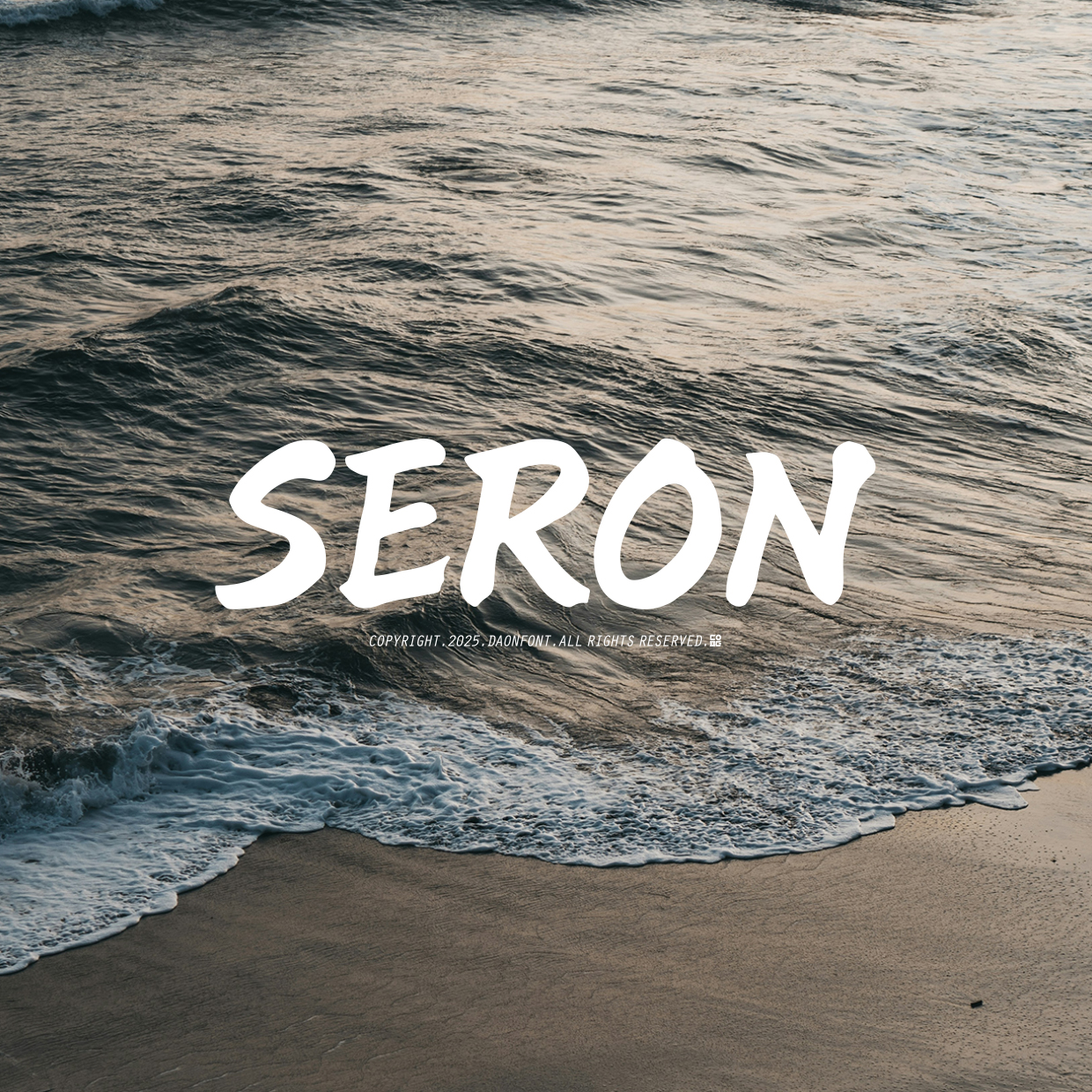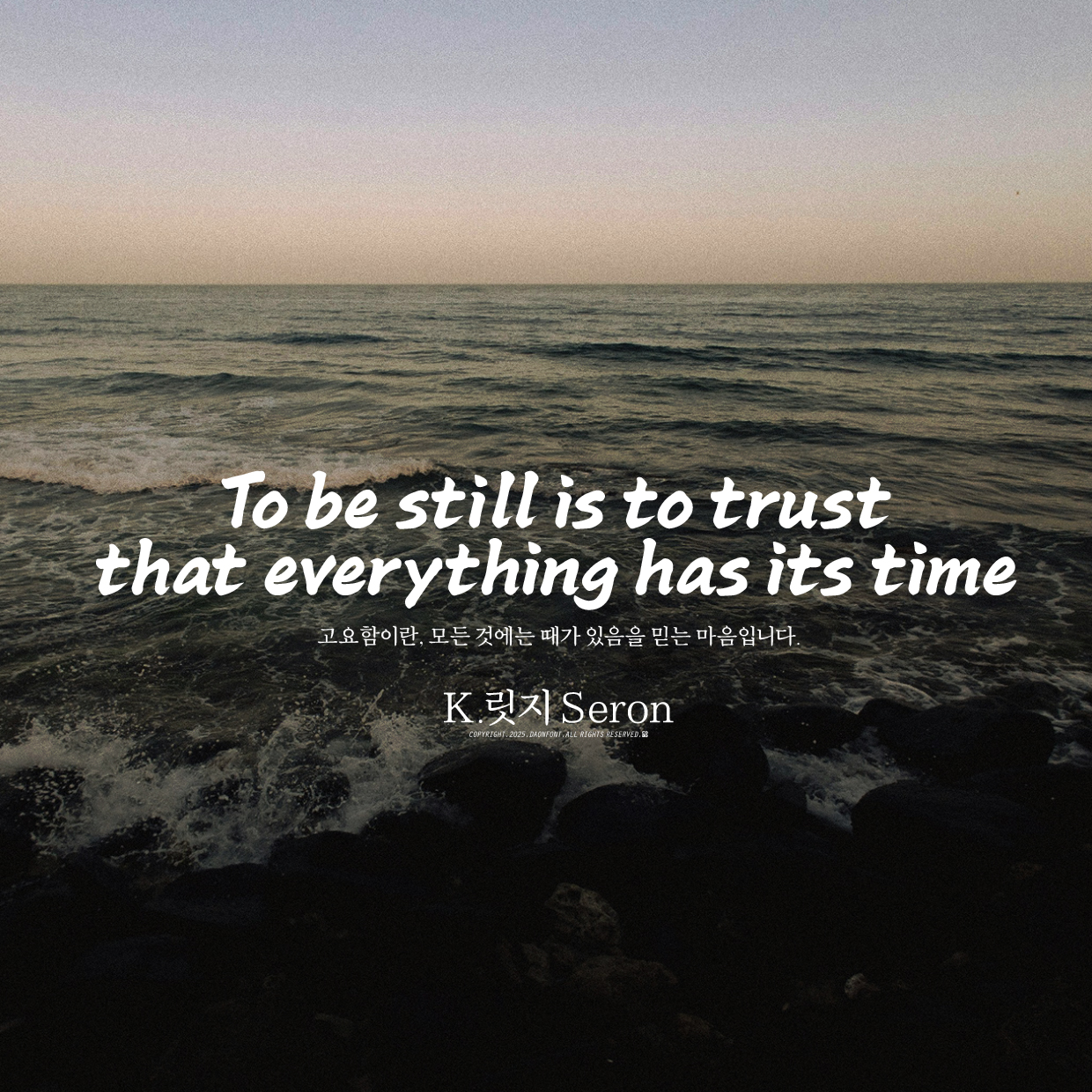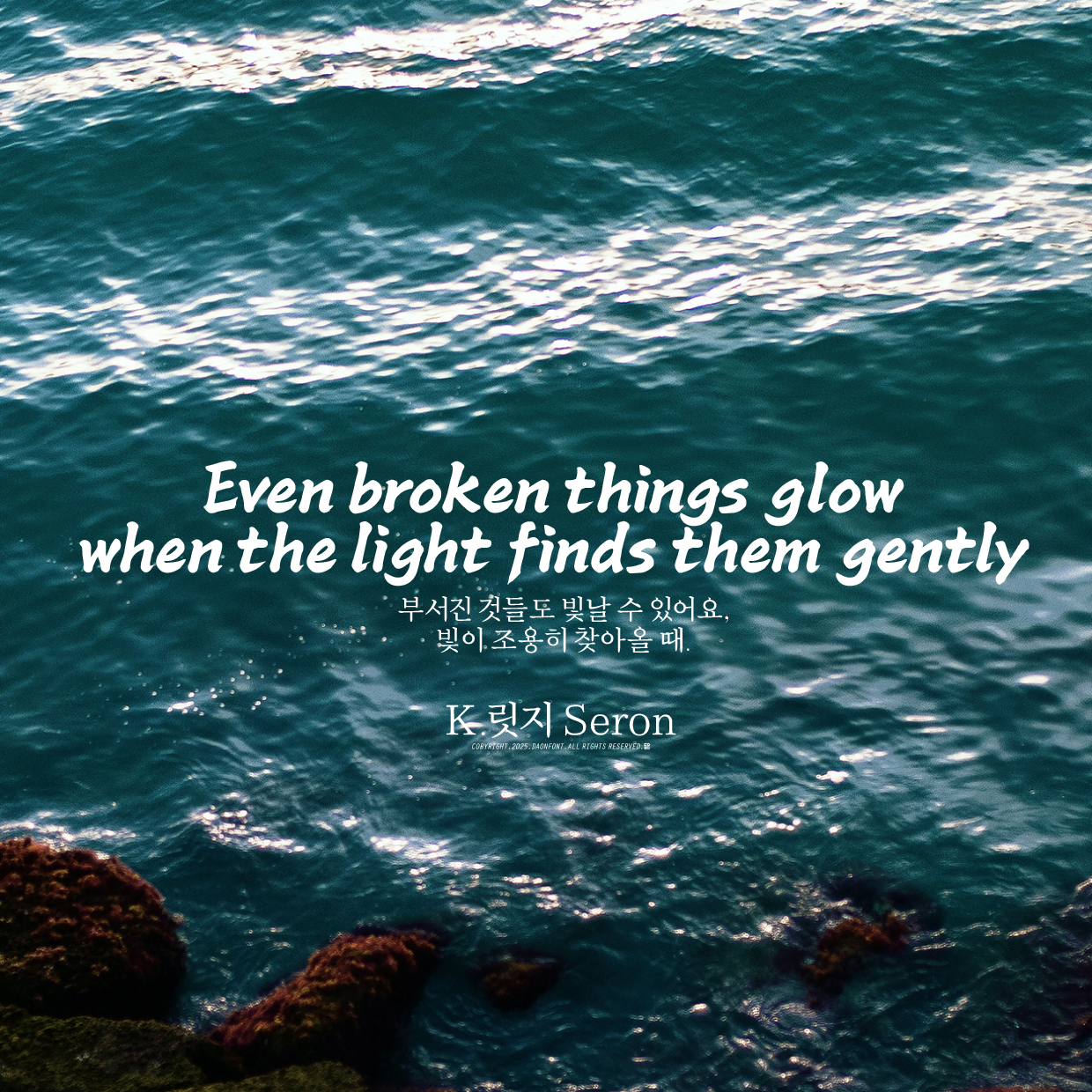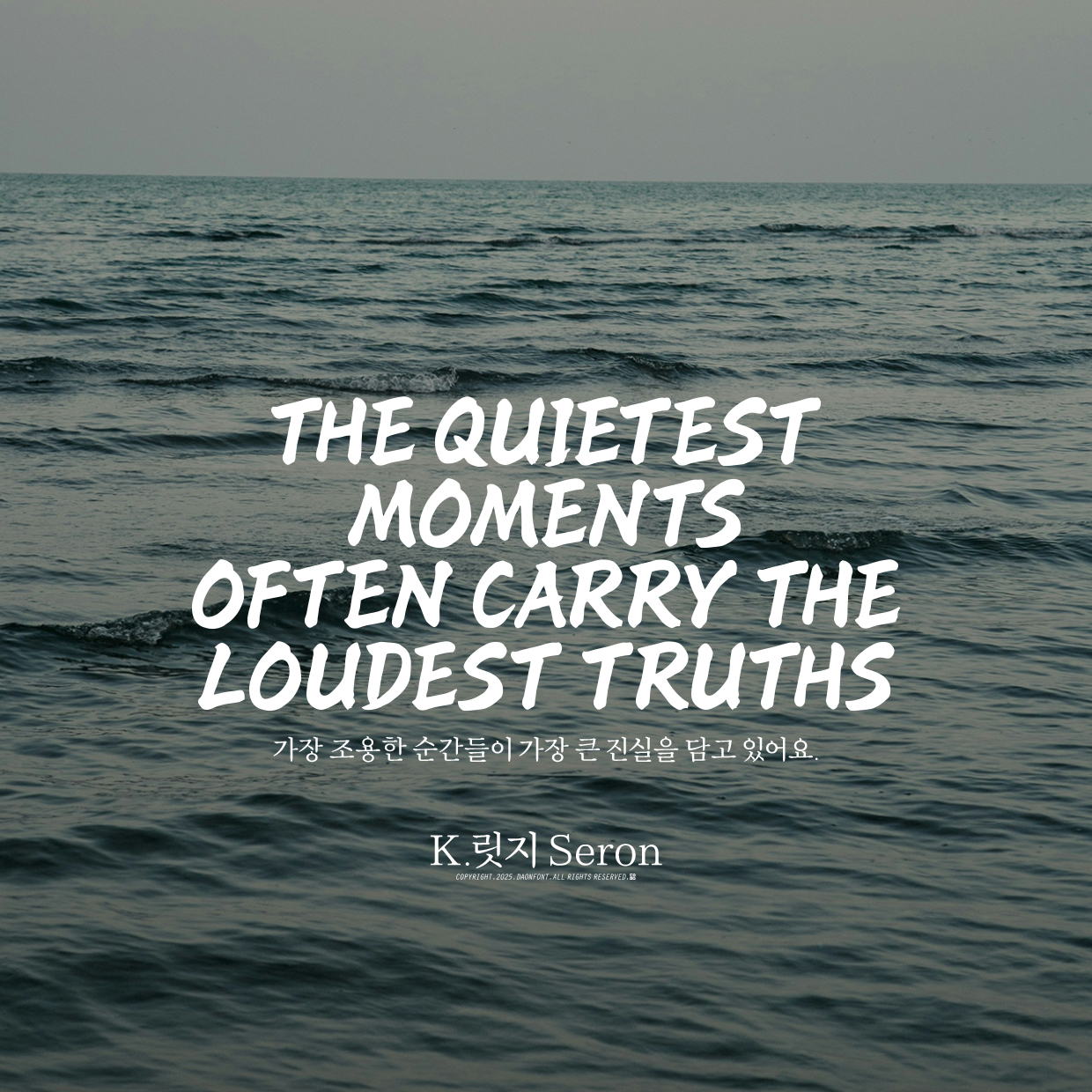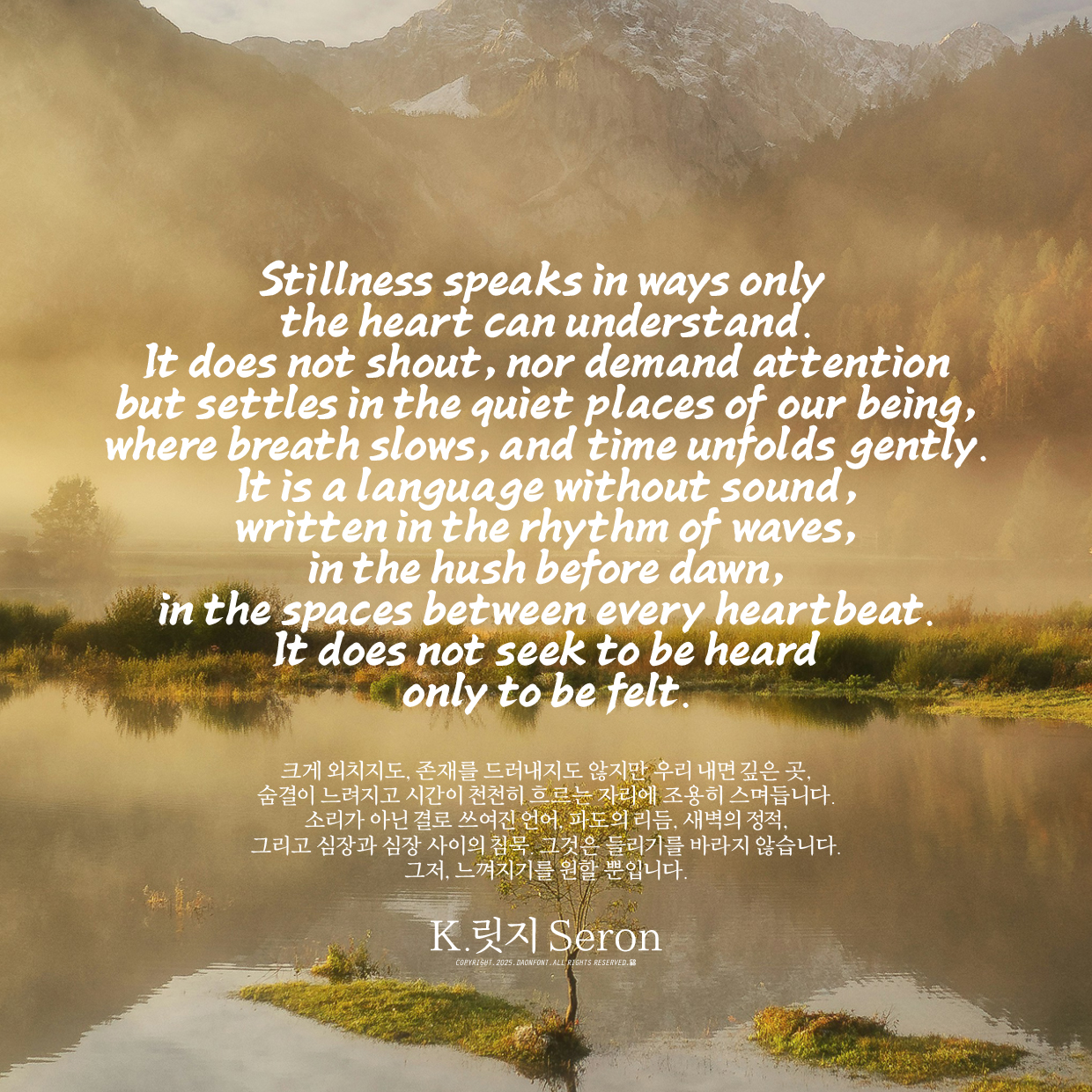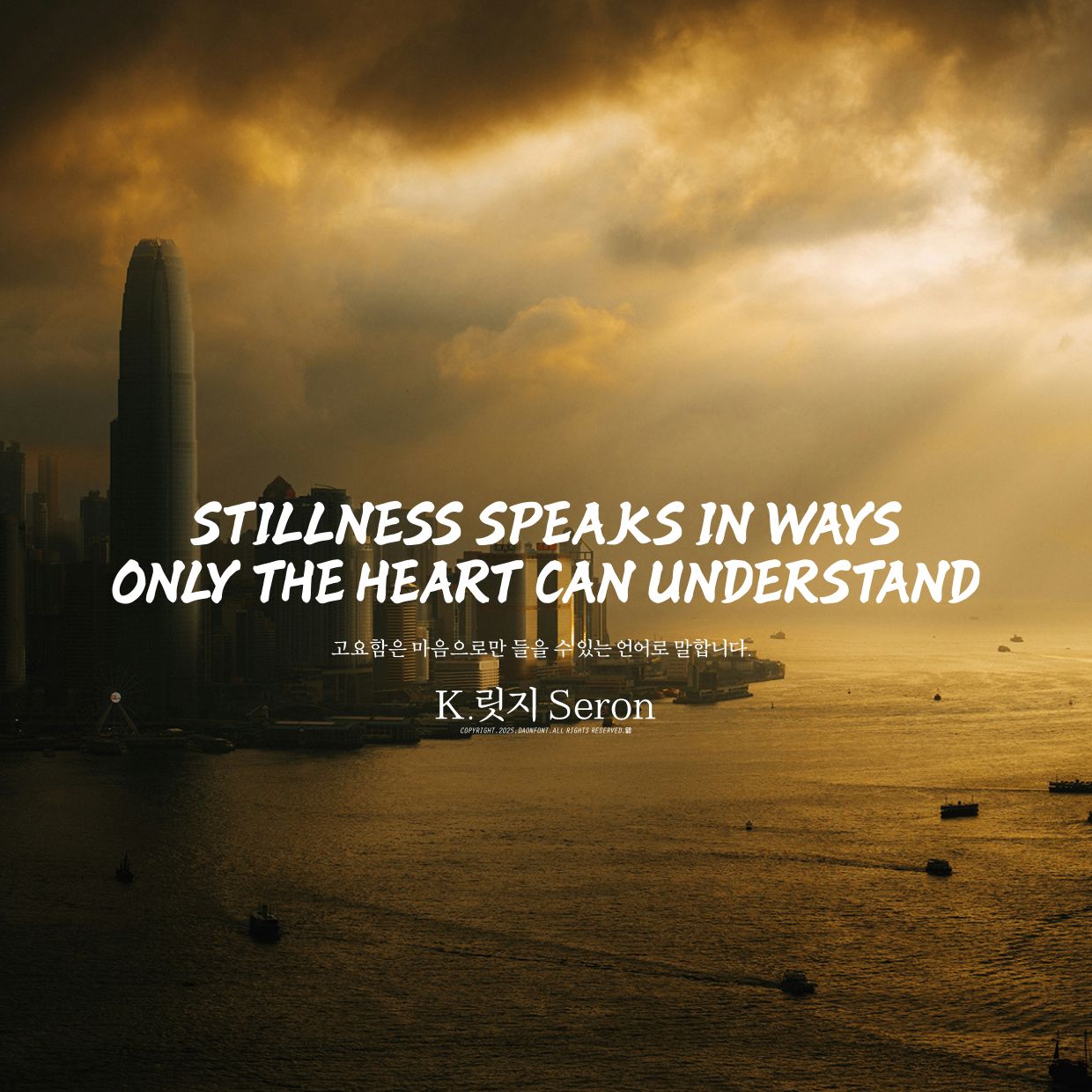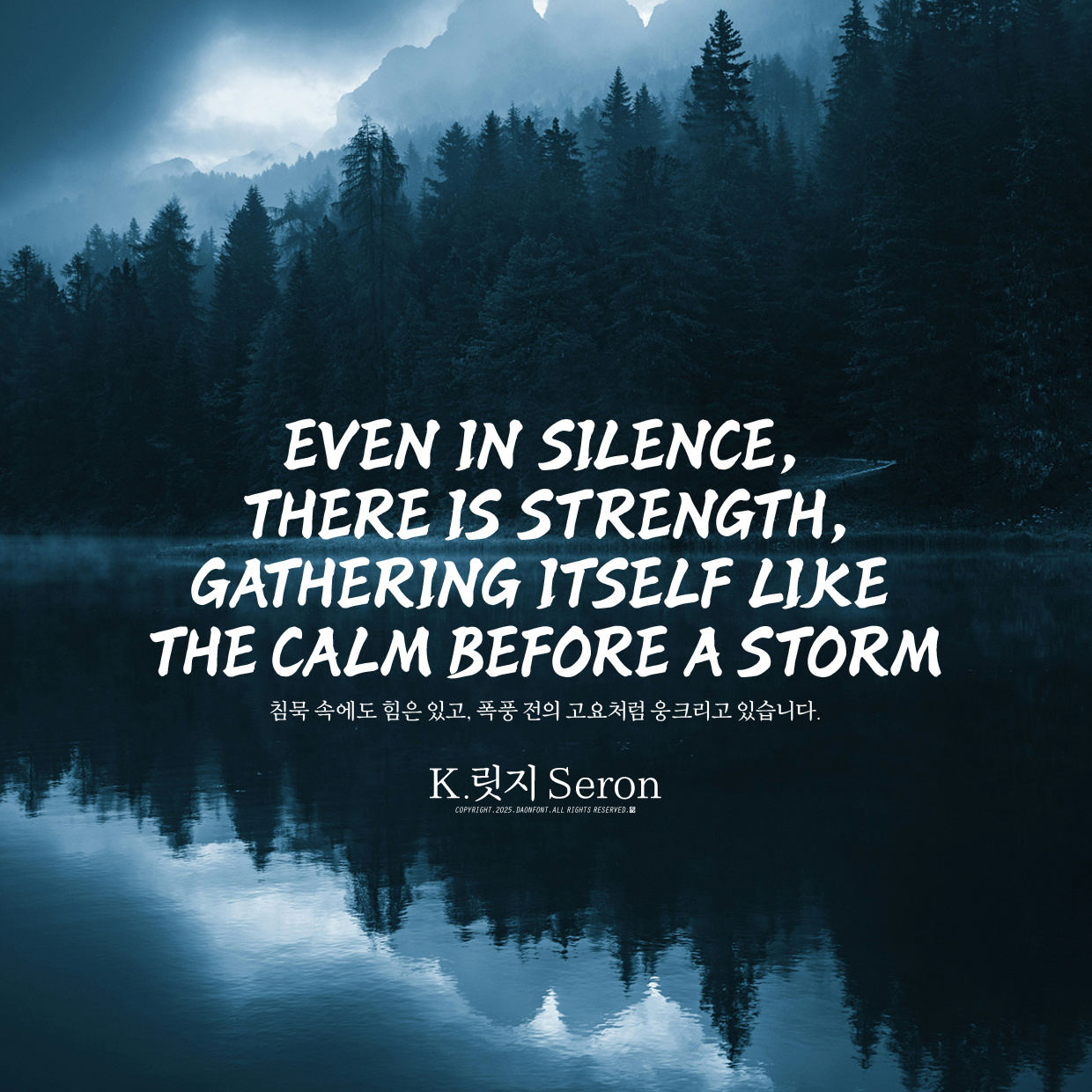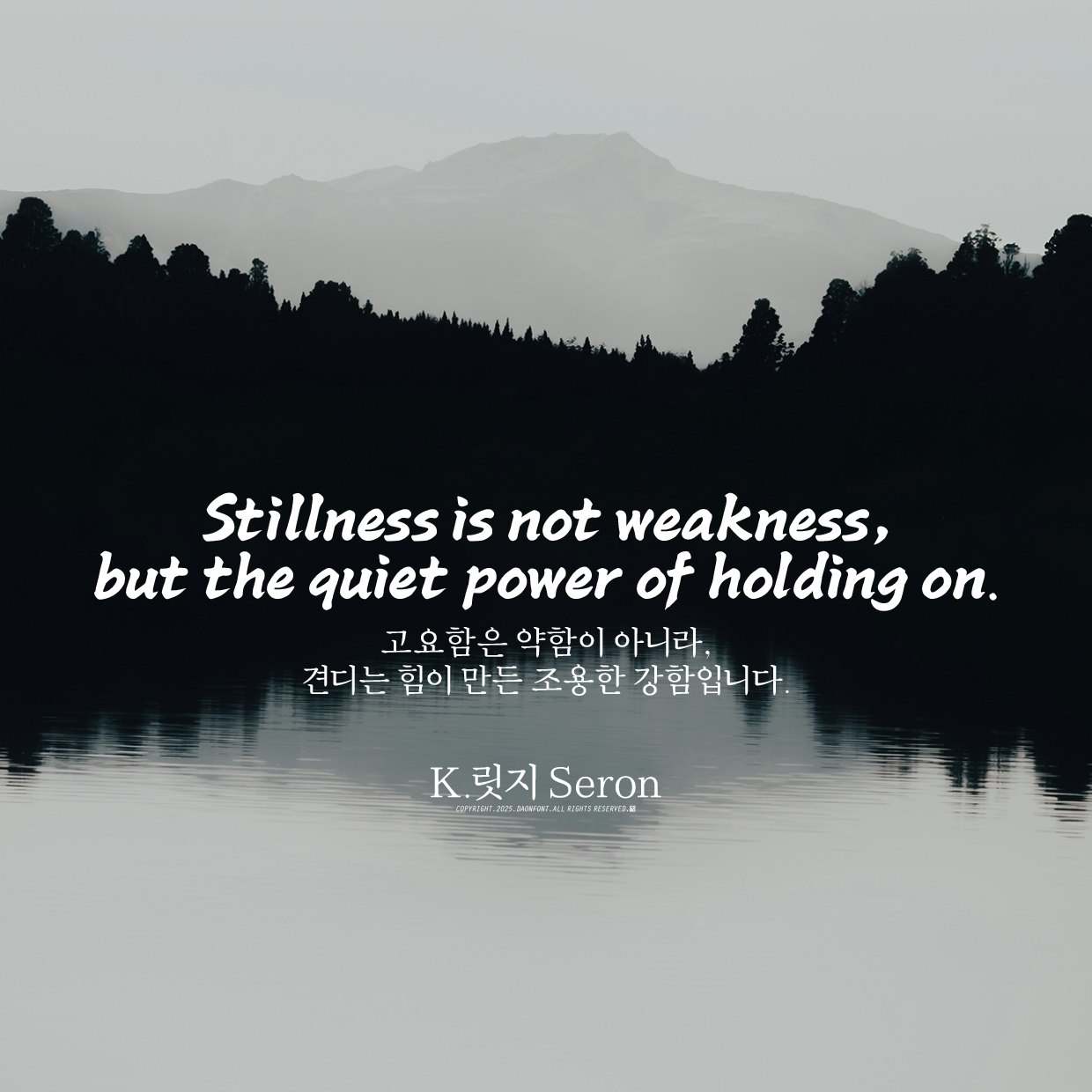
K.릿지 프로젝트 시즌2, 첫 작품 Seron(새런) 소개
Seron(새런)은 고요한 바다와 부드러운 바람에서 영감을 받은 현대적인 브러시 스크립트 폰트입니다.
자연스러운 붓결과 손글씨의 리듬을 담아내며, K.릿지 프로젝트 시즌2의 첫 작품으로서
부드러움과 명료함이 조화롭게 공존하는 서체입니다.
감성을 담은 타이포그래피, Seron.